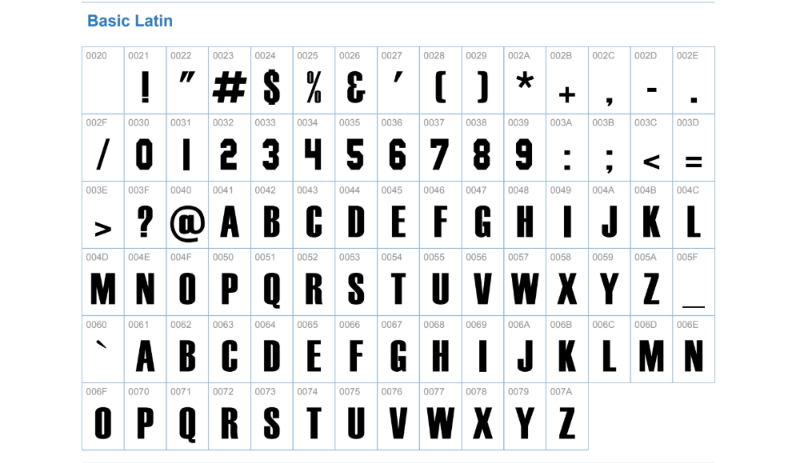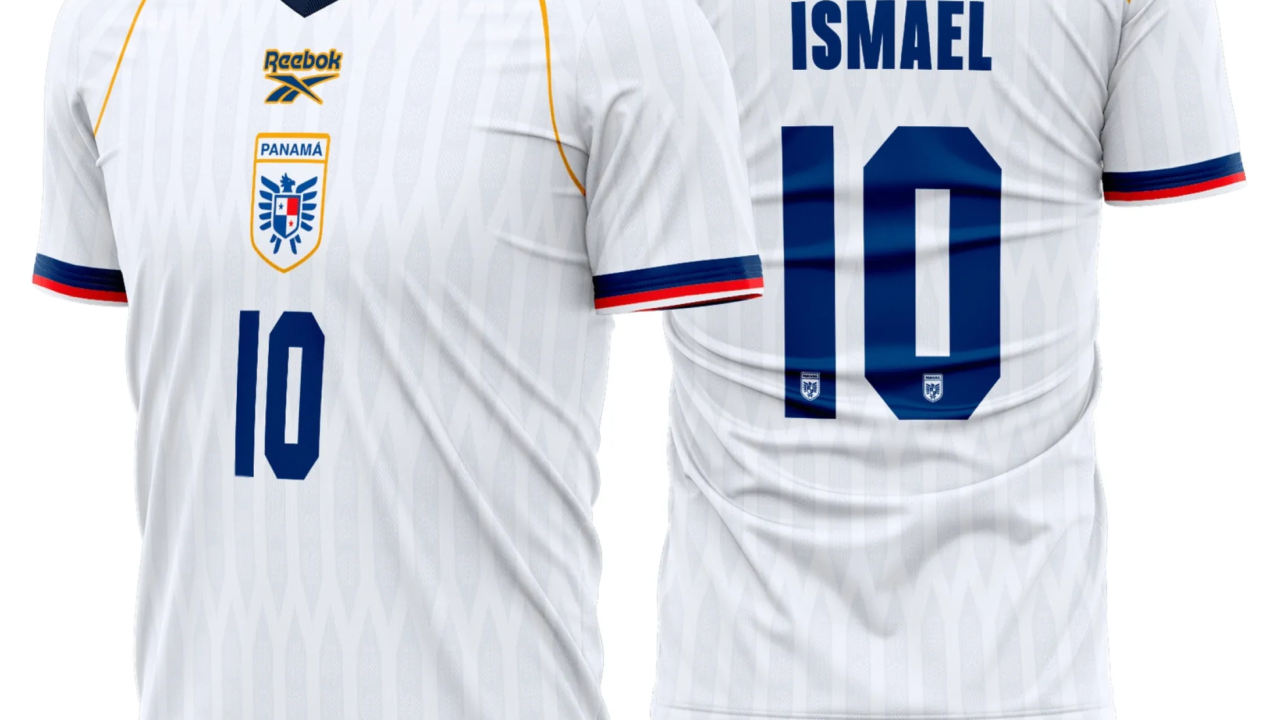
A Copa do Mundo de 2026 está aí e o Panamá chega para sua segunda participação com uma identidade visual que já está dando o que falar. A Reebok, responsável pelos uniformes da seleção canalera, desenvolveu uma tipografia exclusiva para nomes e números que combina tradição e modernidade.
Estilo visual da tipografia
A tipografia do Panamá para 2026 aposta em traços geométricos e cortes retos que remetem à força e à determinação da seleção. Os números têm um design encorpado e blocado, garantindo legibilidade tanto nos close-ups da TV quanto nas arquibancadas dos estádios.
O estilo dialoga com a estética retrô dos uniformes, resgatando a identidade visual que marcou a primeira participação panamenha em Copas. É uma fonte que impõe presença sem perder a sofisticação.
Aplicação no uniforme
- Home (titular): Vermelho tradicional com detalhes em branco e azul marinho
- Away (reserva): Azul marinho com laterais brancas e contorno amarelo
- Third (terceiro): Branco com acabamentos em vermelho e azul
A fonte aparece de forma destacada nas costas das camisas, com nomes e números em alto relevo visual.